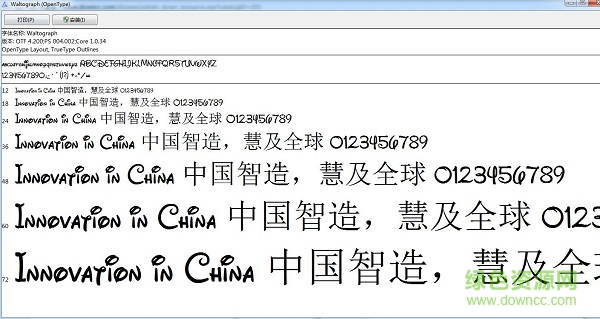
waltograph字體是一款萌萌的的創(chuàng)意字體,用筆生動,字形親切,可以用于表情包制作,卡通圖書、包裝設(shè)計等領(lǐng)域,小伙伴們趕緊下載收藏吧!
waltograph字體給人的感覺是親切、隨意、可愛、呆萌,擺脫了一般字體給人的正規(guī)感,讓人感覺輕松、無憂無慮!